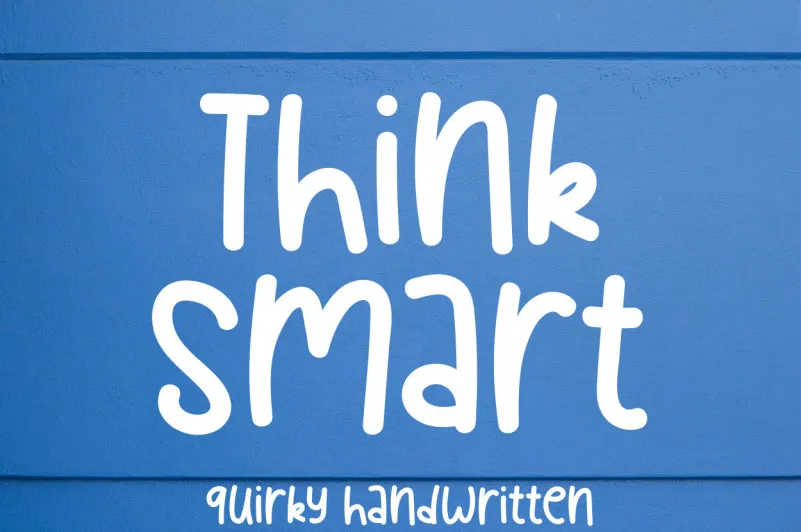
A fonte Think Smart é uma escolha perfeita para seus projetos de design que precisam brilhar com estilo criativo. Desenvolvida pelo designer sugiharto1790, esta fonte está disponível no gênero Display Fonts, o que significa que ela traz um toque único e divertido a qualquer projeto onde é usada. Quiriquiça e simplicidade são as características principais desta fonte. Ela vem em forma de escrita à mão, garantindo uma aparência leve e descontraída sem perder sua legibilidade. Ideal tanto para textos longos quanto para mensagens breves, Think Smart oferece um toque amigável que faz qualquer design se destacar. Para quem está procurando algo diferente na mistura do mundo digital com os traços manuais da escrita à mão, a fonte Think Smart é uma ótima escolha. E seu designer habilidoso sugiharto1790 tornou-a ainda mais especial ao criar esta versão que combina criatividade e simplicidade em um único design.